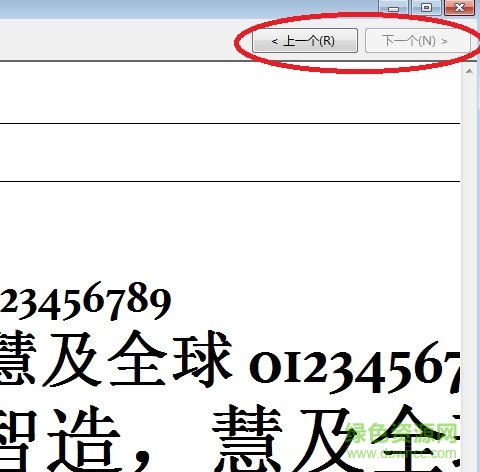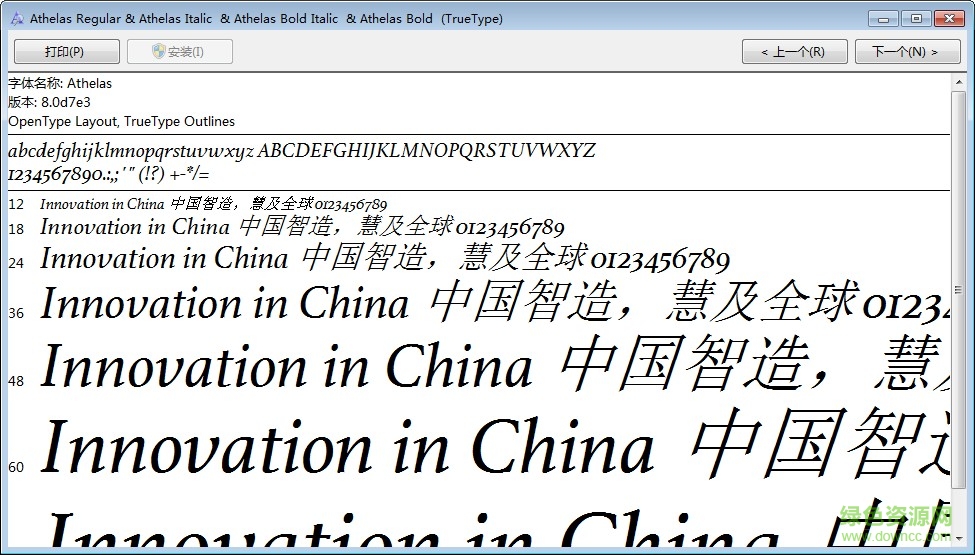
athelas italic字體是一款十分漂亮的英文斜體字體,線條夸張,字形花哨,可應(yīng)用于涂鴉設(shè)計、美術(shù)設(shè)計、創(chuàng)意海報、飾品包裝等眾多領(lǐng)域,歡迎大家在綠色資源網(wǎng)下載!
斜體是在正常字體樣式基礎(chǔ)上,通過傾斜字體實(shí)現(xiàn)的一種字體樣式。 中文(漢字)的斜體實(shí)際上都是單純將字面從正方形改為平行四邊形的“偽斜體”。
傳統(tǒng)排版中,漢字一般不使用斜體。電腦的普及給字體變形帶來了極大方便,才將西文這一習(xí)慣延伸到中文中。